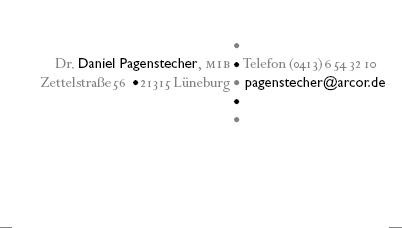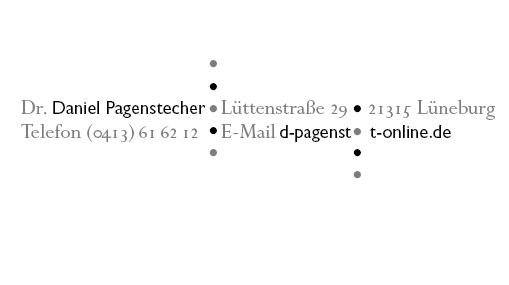
Ich empfinde es tendenziell anders herum. Ich finde bei E-Mail-Adressen wie ,  etc. müsste man meiner Meinung nach nicht noch auf die Seite http://www.homepage.de hinweisen. Das sollte eigentlich jeder selber hinbekommen. Trotzdem habe ich sie hingeschrieben, um der Konvention genüge zu tun. Platz genug ist ja ;)
Ich hatte genau diese Hoffnung, als ich meine Ebay-Auktionen überarbeitete. Ebay verbietet direkte Verweise auf eine Webseite in der Auktion. Gewerbliche Anbieter müssen jedoch ein Impressum angeben.
Also dachte ich, daß info(at)bleisetzer.de genüge, um auf meine Seite zu verweisen.
Es kommen jede Woche Anfragen, wie denn meine Webseite heiße, die ich in den Auktionen erwähne.. seufz.
Als ich mich selbständig gemacht habe und ein »Logo« brauchte, war schnell klar, dass ich mein Kürzel, das ich bis dato verwendete um meine Zeichnungen zu signieren, zu meinem »Markenzeichen erhebe«. Es ist ein verschlungenes SJ dar. Selbst bei der Wortmarke habe ich mir Gedanken gemacht. Tradition und Moderne (Antiqua und Grotesk) verbunden mit einer persönlichen Note (das »handschriftliche« SJ und das Plus). :roll:
Ehm.. oh ja, natürlich.. :oops:
Hier der Schritt zurück, was ist von so etwas zu halten?
=> ist freilich auch noch nicht tiefenvermessen, da ja die Daten noch zu ändern sind und sich die langwierige Positioniererei erst mit den echten Daten lohnt. Habe ich abge-
Kupfers: (nur das Grün ging nicht) Buchstabenkommenseltenallei n, daher die Pünktchen :) (zu viele?) Das Buch ist für mich noch immer eine typografische Augenweide, die ich extrem pfleglich behandle, damit in der täglichen Hektik ja keine Farb-, Tinten oder Kleisterkleckse drauf kommen oder gar eine Seite knickt! Von den Unmengen Büchern in den Regalen erfährt nur ein gutes Duzend eine solch pflegliche Behandlung. Eine sehr schöne Arbeit!
Bleisetzer: Preußen und Futura => originelle Mischung! (hätte da eher mit etwas Gebrochenem gerechnet ;) )
Warum der *doppelte* Wechsel (Farbe *und* Typo)???
Reicht nicht eines allein? Farbe.
Und • statt @ - überzeugt mich nicht, es gibt immer noch Menschen (Verleger!), die sich ALLE E-Mails von Ihrer Seketärin ausdrucken lassen, weil sie's nicht selbst hinkriegen ...
Typo-"Benimmregel" von früher: den eigene Name nicht in fetter Schrift setzen. Gilt das noch in Preußen?
das habe ich ja noch nie gehört, wo steht das denn? ich finde das kann man nicht pauschalisieren, der name ist mind. genauso wichtig wie das logo der firma, weil es der ansprechpartner ist.
@ frau kupferschmid, den | zwischen der vorwahl und der nummer habe ich auch noch nie gesehen. :?
wir trennen hier telefonnummern nur, wenn a) es der kunde unbedingt will, wie auch immer oder b) es mir logisch erscheint 2 stelle von hinten.
z. b. 22 33 44 es sei denn die nummer geht lautet so: 222 33 4 ansonsten halte ich mich an die neue regel: alles zusammen.
Hier der Schritt zurück, was ist von so etwas zu halten?
=> ist freilich auch noch nicht tiefenvermessen, da ja die Daten noch zu ändern sind und sich die langwierige Positioniererei erst mit den echten Daten lohnt. Habe ich abge-
Welche Funktion sollen die vertikalen Reihen der fetten Punkte symbolisieren? Sie zerschneiden die Email-Adresse.
"Weißräume wirken lassen" das gefällt mir grundsätzlich gut.
Aber Dein Zweizeiler mit den beiden Vertikalen quetscht die Informationen sehr zusammen.
Preußen gab es fast 500 Jahre lang.
Da passen sehr viele Schriften rein, auch Gebrochene, aber auch die Futura. In meinem Fall gerade die Futura.
Nun nochmal mein Senf zu den bisherigen Beiträgen zusammengemanscht:
Wir machen hier keine Kunst, sondern Werbung. Funktion geht über Form (hatte wir ja schon mal).
Den Namen hervorzuheben halte ich für sinnvoll. Der Name ist nach dem Firmennamen die zweitwichtigste Information, manchmal sogar die wichtigste. Benimm-Regeln hin oder her – nach dem Namen wird gesucht.
Telefonnummern teile ich so auf, daß sie sich optimal merken lassen. Regen hin oder her. Eine Ausnahme würde ich (vielleicht) nur bei der Firma DUDEN machen.
An Tobber: das @ der E-Mail-Adresse wegzulassen halte ich für gefährlich. Es gibt einfach noch zuviele Leute, die mit dem Web und dem ganzen virtuellen Kram nicht so vertraut sind. Die schnallen das u.U. nicht. Schön finde ich das Hervorheben der wichtigen Informationen.
Nur so meine zwei Pfennige.
Ja, die Doppelachse quetscht und ja, das @ muss wohl mit hinein ... vielleicht ja so:
Prinzipiell halte ich die doppelte Betonung auch für übertrieben. In dem Fall jedoch soll Name und E-Mail (eigentlich die einzig relevanten Informationen) sofort -- also wirklich auf dem allerersten Blick -- erkennbar sein. Insofern gewollt.
Wir fahren nun nächste Woche auf die Buchmesse (Pflichttermin f. Autoren) und die Herrschaften wollen "etwas andere" Visitenkarten und baten mich mir mal Gedanken zu machen. Das ist also nix für Kohle -- eher ein geschuldeter Gefallen.
Weshalb ich dies erzähle? Es sind zahlreiche Entwürfe von Caflisch ausgestellt, unter anderem auch für Visitenkarten. Die Skizzen – und vor allem Schriften! – sind so passgenau gezeichnet, dass der Setzer es nur noch auszuführen hatte. Steht man vor so einer Vitrine, in der z. B. eine Garamond-Schrift exakt und in der richtigen Größe gezeichnet ist, und daran denkt, wie planlos man selbst manchmal am Computer herumprobiert … Manchmal täte es gut, wenn das Material einem noch – wieder – etwas Widerstand entgegenbrächte.